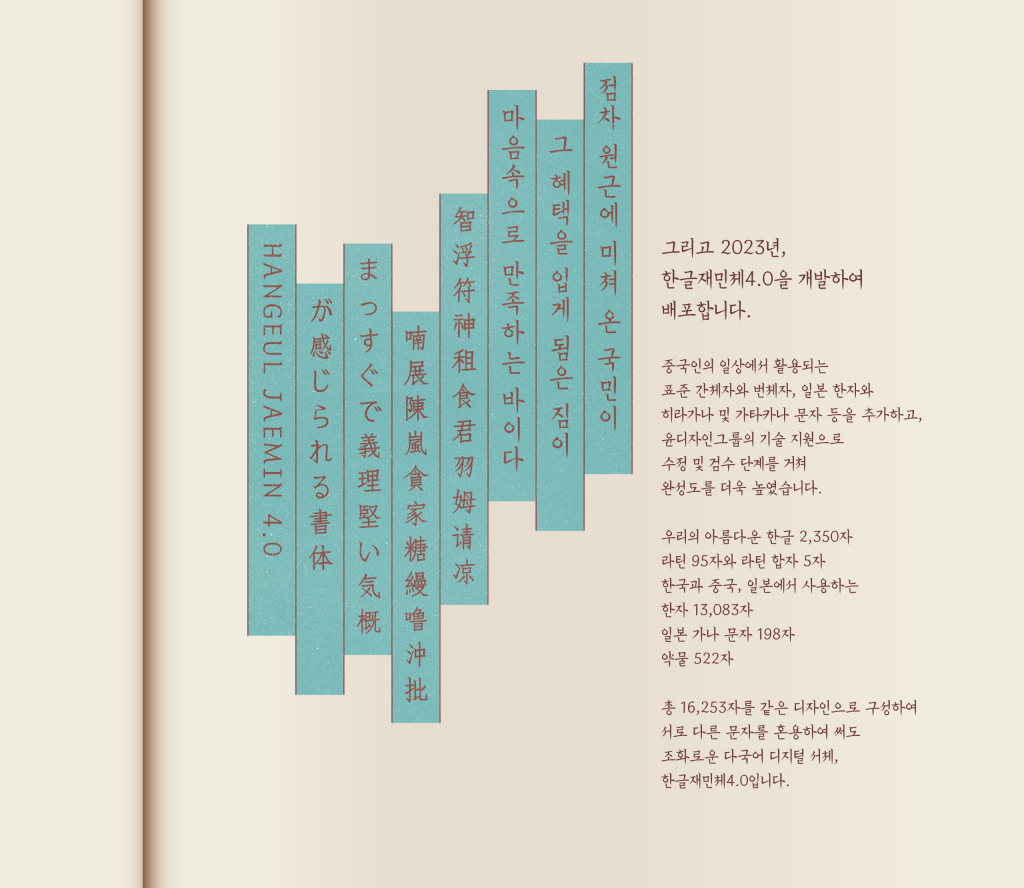
韩契在民体(韩文名:한글재민체)是基于1908年颁布的《大韩国会开幕原则书》(国家注册文化财第449号)中的毛笔字字体,由朴载甲前首尔大学医学院教授和金敏国民大学技术设计专门大学院院长共同开发。2020年在韩文字日发布了韩契在民体1.0,2021年增加了KS标准汉字的韩契在民体2.0,2022年又增加了韩国独有的203个汉字和大法院人名用8289个汉字等,发布了升级版的韩契在民体3.0。而由尹设计集团于2023年发布的韩契在民体4.0,增加了中国人日常使用的标准简体字和繁体字、日本汉字以及平假名和片假名等。通过这样的设计,完成了支持多语言的数字字体,包括韩文、拉丁字母、中国的简体字和繁体字、日本文字等,都采用相同的设计。